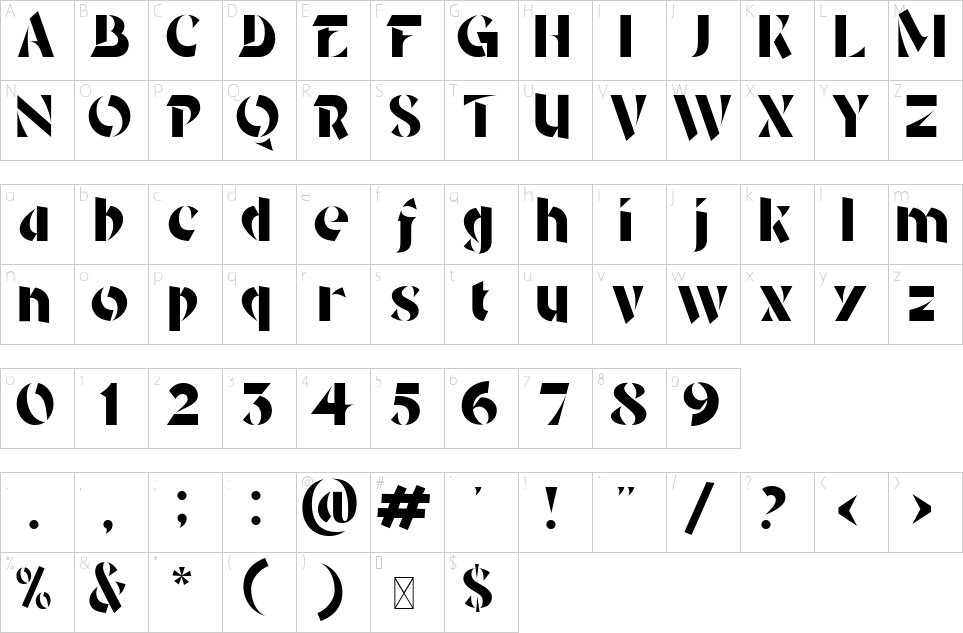
A fonte ‘Tabela’ é uma opção agradável para aqueles que estão procurando por uma fonte de fácil leitura para textos em sites, blogs ou documentos. Desenvolvida pela 177Studio.com, ‘Tabela’ foi projetada para ser legível e fácil de usar, independentemente do dispositivo que você está utilizando. Esta fonte é especialmente útil para designers gráficos e escritores digitais que buscam uma fonte moderna e clara para suas necessidades diárias. Com mais de 3.957 downloads, é claro que muitos usuários encontraram esta font adequada para seu propósito. ‘Tabela’ é uma opção gratuita e eficaz para quem busca uma solução prática para a tipografia da web.